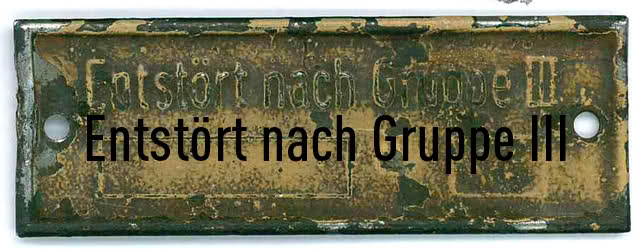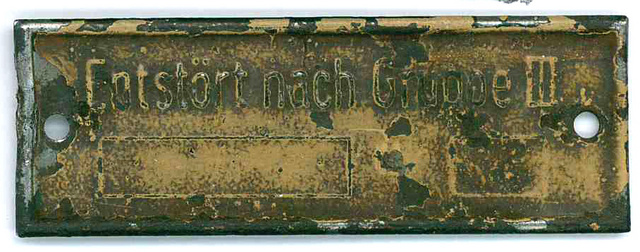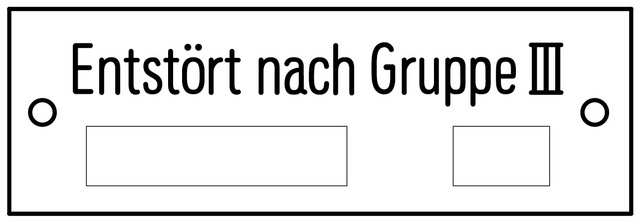
Schrift aus der Vorkriegszeit?
Hallo, wer kennt die Schrift auf diesem Metallschild? Das Schild gehört zu einem Wehrmachtsmotorradgespann (BMW oder Zündapp). Ein Liebhaber solch eines Motorrades möchte das Schild erneuern. Und es muss alles original sein. Wer kann mir Auskunft geben?
ich rekonstruierte mal Beschilderungen und Beschriftungen der Luftwaffe (1933–1945) vor vielen Jahren, IIRC wurde in den Original-Schriften die DIN 1451 fette Mittelschrift vorgegeben.
Zur Datierung des Schildes: da man Reste von Dunkelgelb erkennen kann, kann man es auf den Zeitraum nach Februar 1943 datieren. Denn ab Feb.43 ersetzte das Dunkelgelb den dunkelgrauen Grundtarnanstrich (-> russische Grassteppen). Möglich ist natürlich auch eine spätere Umlackierungen eines früher gefertigten Fahrzeugs. Gemäß der Datierung kann man die entsprechende Ausgabe einer DIN wählen (bei meinem Projekt Ausgabe 1940). Ob allerdings kleine Zulieferbetriebe sich immer an die Vorschriften hielten, kann bezweifelt werden.
Hallo, danke für die wunderbare Antwort. Aber leider passt die DIN 1451 nicht mit dem Original überein. Der Zündapp-Liebhaber besteht auf die Originalschrift. Da bleibt mir nichts weiter übrig, als die Schrift nach zu bauen. Schade.
Die DIN Condensed geht schon in die richtige Richtung. Ob die abweichenden Details durch den Herstellungsprozess bedingt sind, sich im Lauf der so eingeschliffen haben oder die Schrift für den Guss optimiert wurde, weiß keiner so genau …
Die Condensed ist relativ nah am Original, aber eben nicht wie das Original. Wenn es Ergebnisse gibt, zeige ich sie gern.
… Die Condensed ist relativ nah am Original, aber eben nicht wie das Original. …
Da stell ich mir als Pedant die Frage, ob das Original überhaupt original ist. Oder ob nicht vielmehr von einem Metallwerker die Schrift an die technischen Anforderungen herangefeilt wurde und möglicherweise jede Charge dieser Schilder anders aussah.
Hallo! Nachfolgend seht ihr das Ergebnis. Ein Foto der Maschine habe ich leider noch nicht.